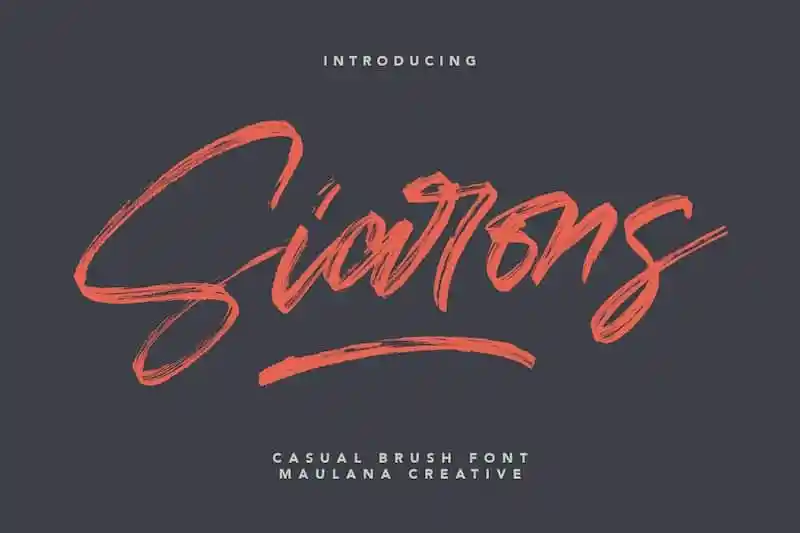
Siarons Brush Font – Download Grátis
A fonte Siarons Brush Font é uma atração visual que captura os sentimentos do mundo contemporâneo enquanto traz um toque romântico e sofisticado. Cada caractere desta elegante fonte, criada pela Maulana Creative usando técnicas de desenho a mão com estilo pincelado, oferece uma experiência única e autêntica, perfeita para textos importantes ou artesanatos que buscam um ar intimista e sofisticado. Seja em uma revista cultural ou num projeto gráfico criativo, esta fonte irá destacar seu trabalho com uma graça singular e modernidade inconfundível. Ela é perfeita para quem busca uma fonte que transmite elegância e luxo, oferecendo um toque especial a qualquer texto, transformando cada palavra em uma pequena obra de arte no papel.